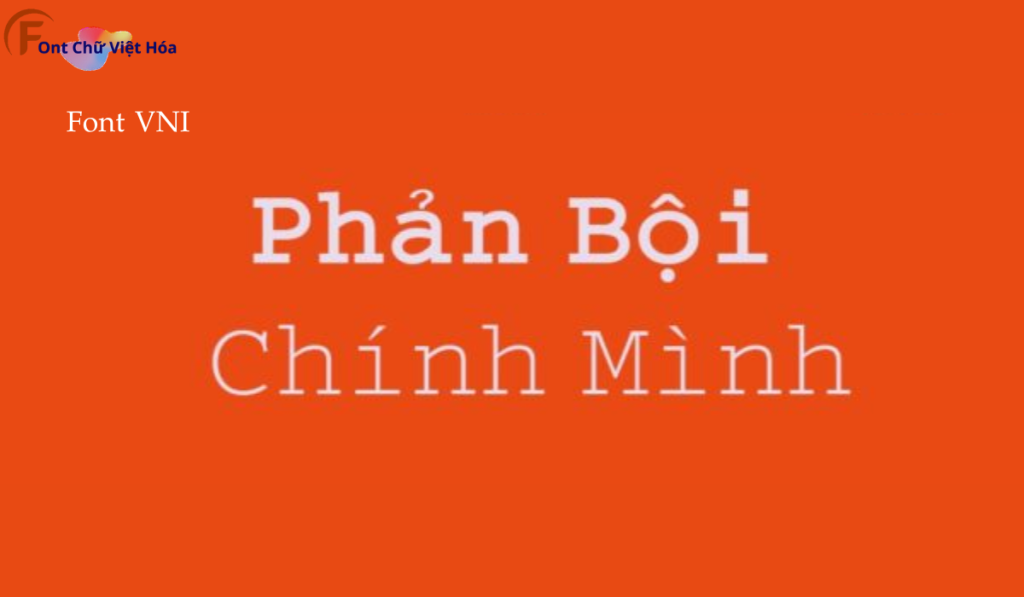
Font VNI Courier Việt Hóa
Kiểu chữ: Kiểu chữ có chân
Font VNI Courier Việt Hóa, thuộc bộ font VNI, mang phong cách cổ điển và chuyên nghiệp, lý tưởng cho các dự án thiết kế như tài liệu văn phòng, báo cáo, và bìa sách. Với các nét chữ có chân và độ dày đều đặn, Font VNI Courier Việt Hóa không chỉ dễ đọc mà còn tạo cảm giác lịch lãm và chuyên nghiệp. Việc Việt hóa font giúp người dùng dễ dàng tích hợp vào các thiết kế tiếng Việt, mang lại sự tiện lợi và nâng cao tính thẩm mỹ.